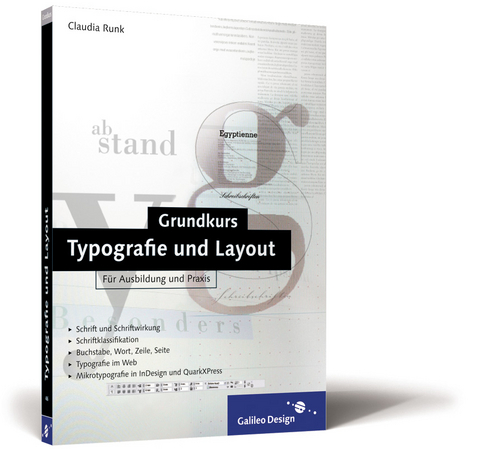
Grundkurs Typografie und Layout
Typografie und Layoutgestaltung – wer ist bei diesem Thema nicht froh, stets ein verlässliches Nachschlagewerk zur Hand zu haben. Wie war das noch einmal mit der Spationierung? Welcher Abstand kommt zwischen "z.B."? Welche Schrift passt auf meinen Flyer, und woran erkenne ich das? All diese Fragen und weitere rund um Textausrichtung, Wort- und Zeilenabstand beantwortet die Autorin. Im Layout-Teil geht es um Gestaltungselemente wie Raum, Linien, Formen, aber auch konkret um Grundlinienraster, Seitenformate und Spalten. Claudia Runk gelingt es, Ihnen ein Gefühl für Gleichgewicht, Kontraste und Betonung zu vermitteln. Beispiele aus Print und Internet, umgesetzt mit unterschiedlichen DTP-Programmen wie QuarkXPress und InDesign vervollständigen das Buch. Dieser praktische Begleiter beweist, dass Typografie Spaß macht und Ihre grafischen Werke verbessert, wenn man sie beherrscht – und genau das lernen Sie hier.